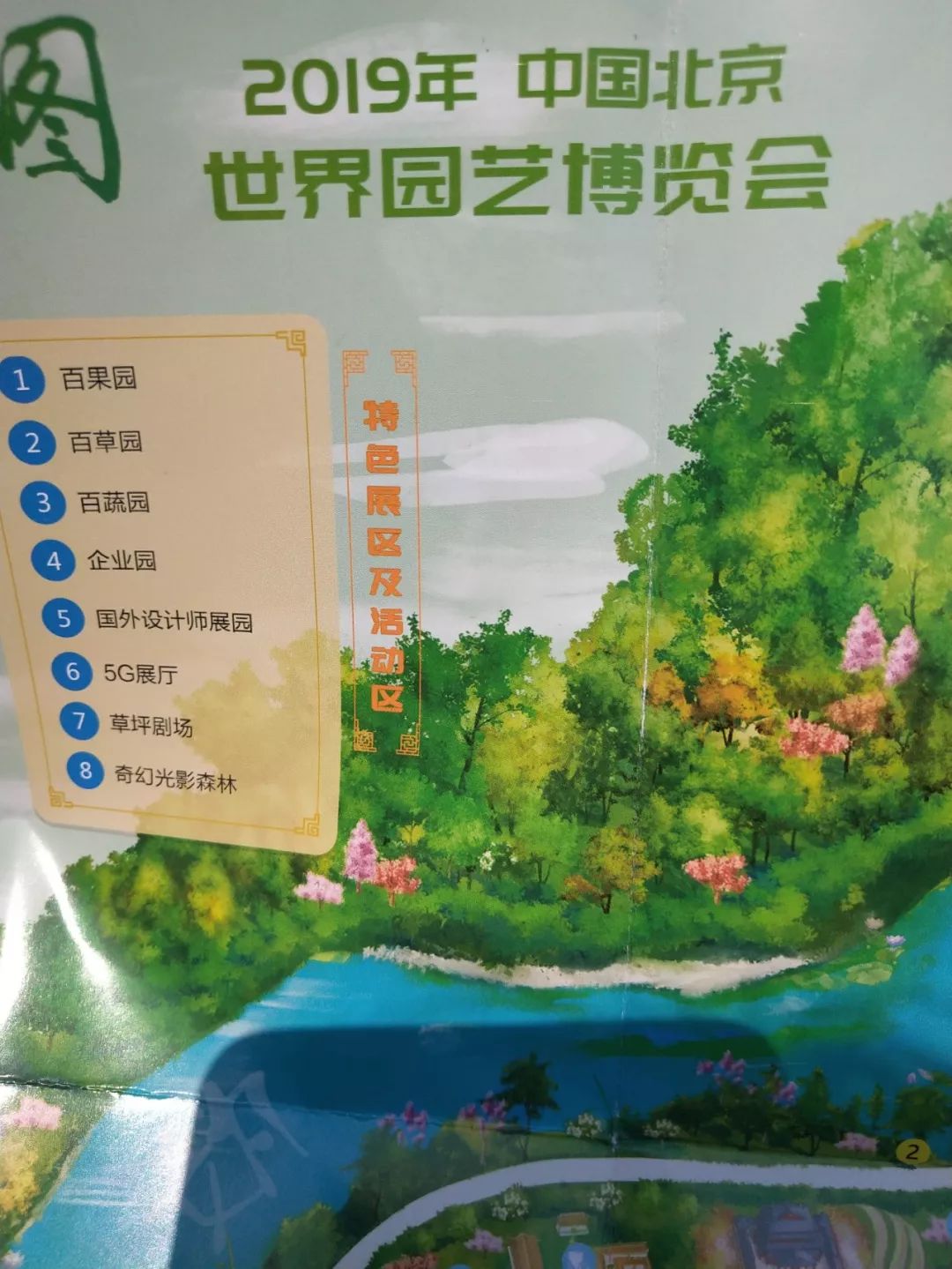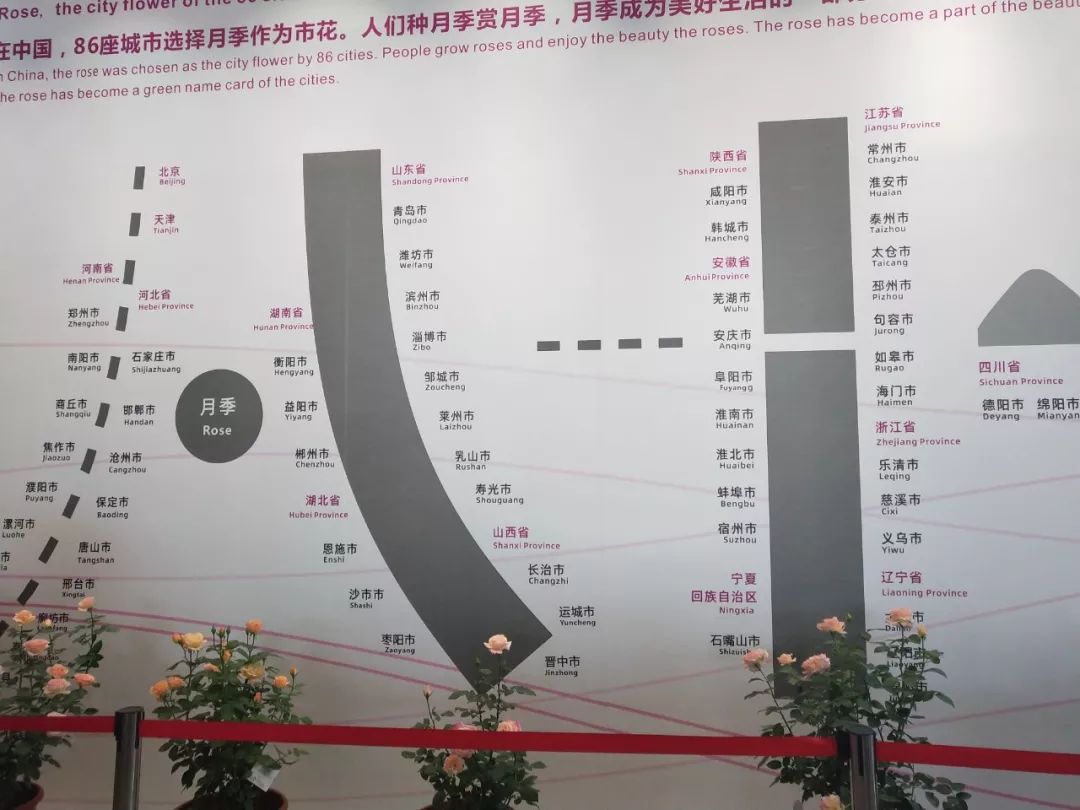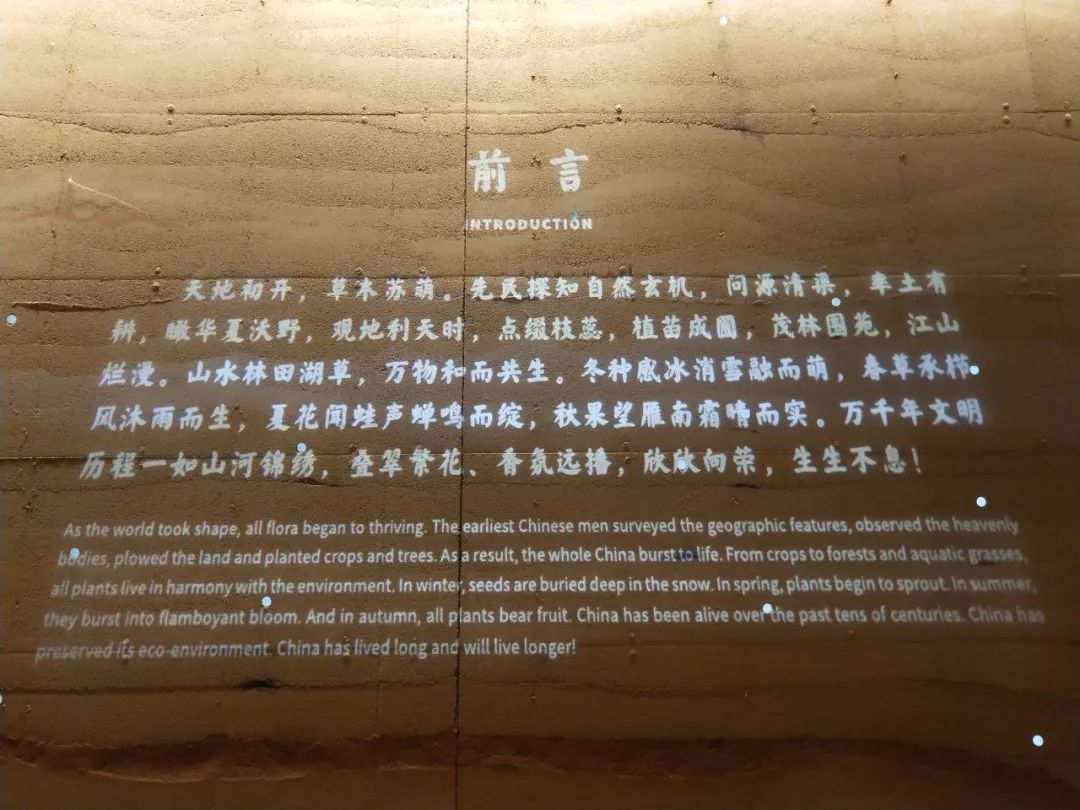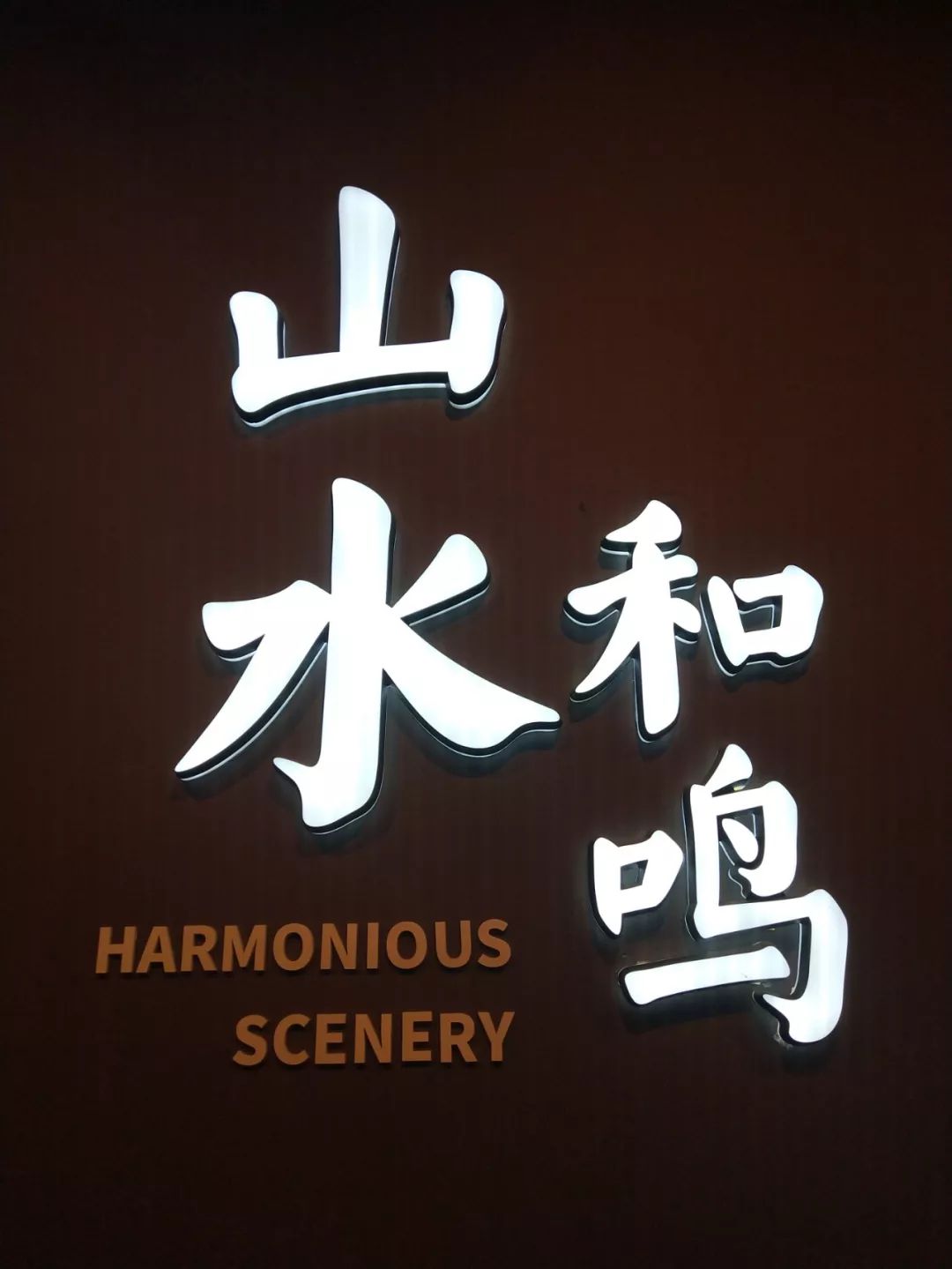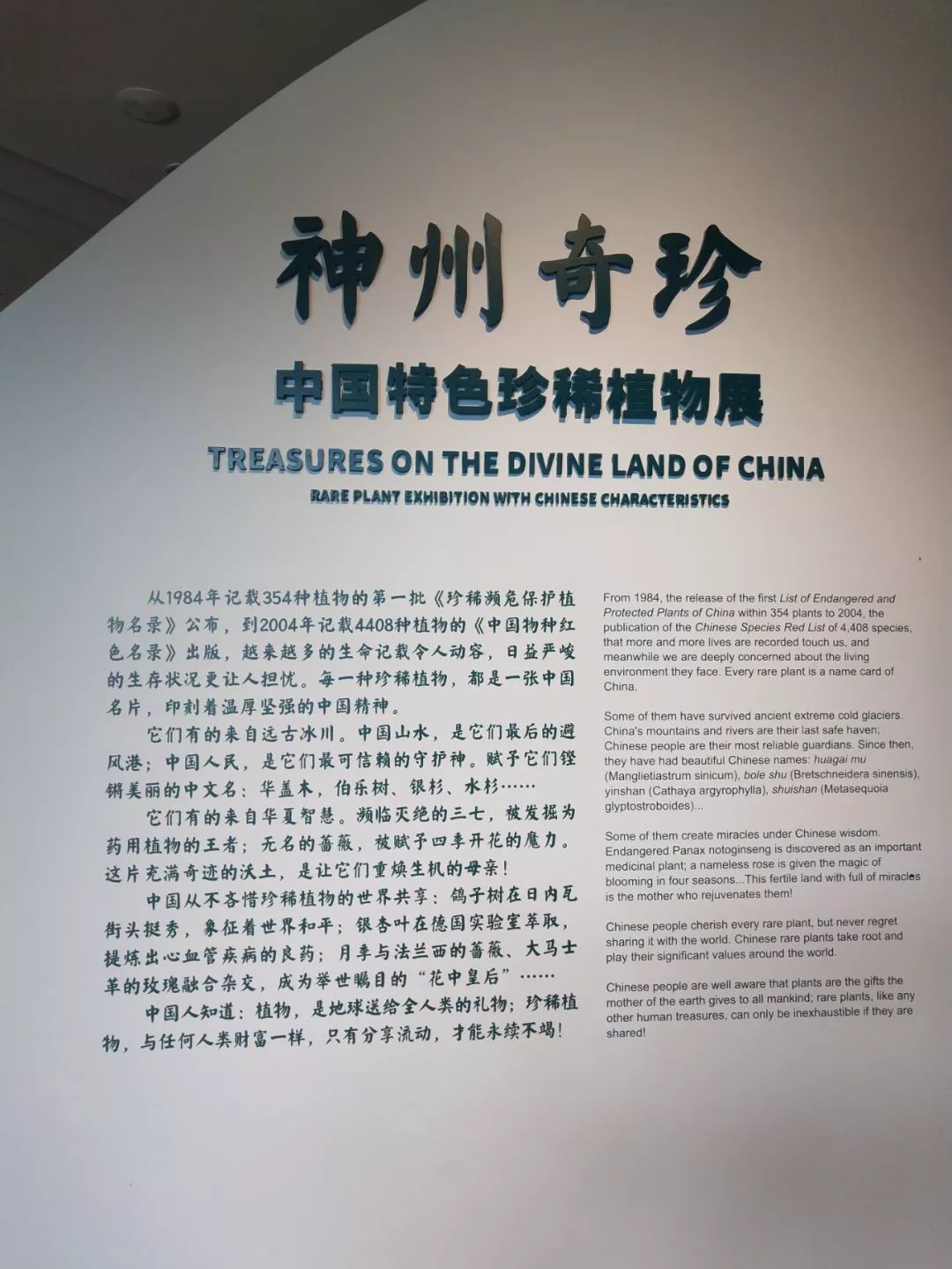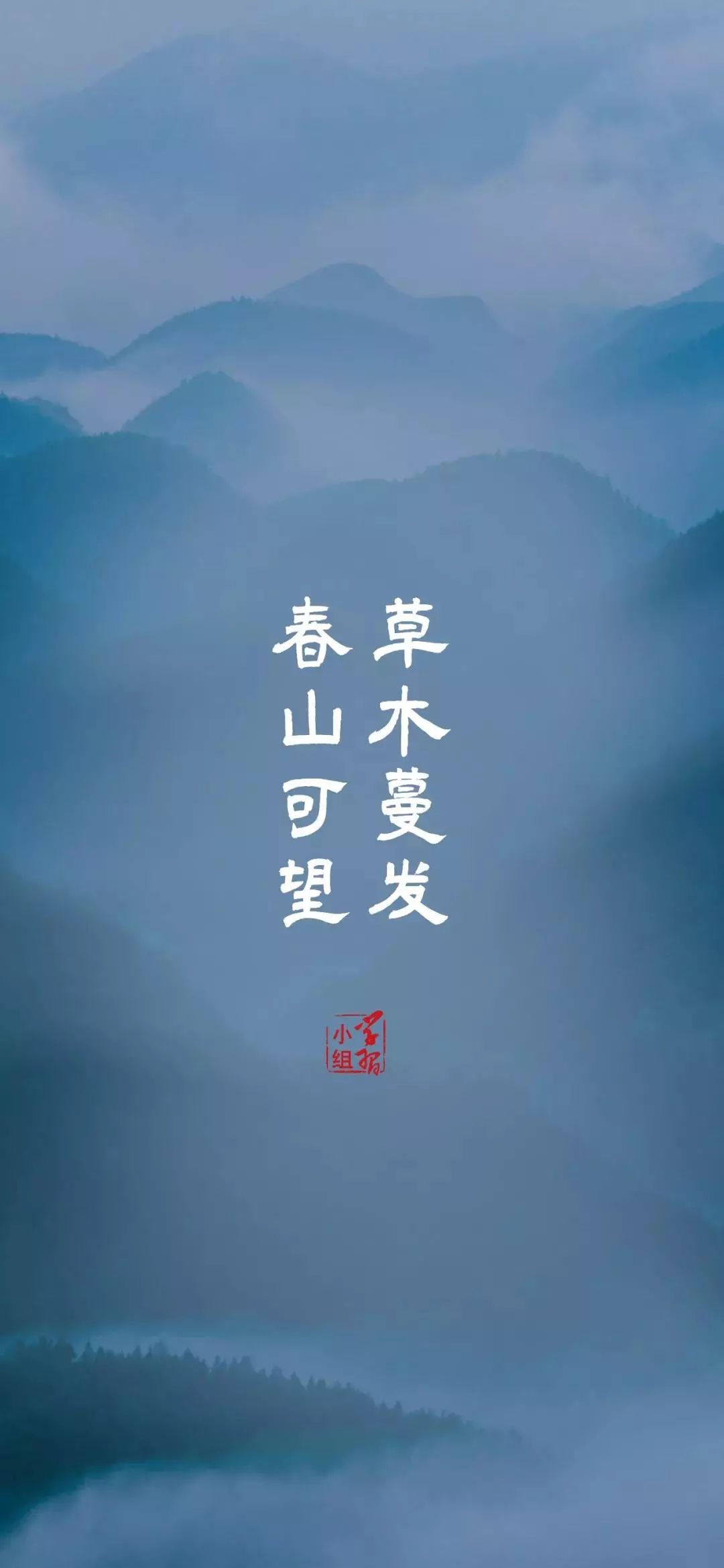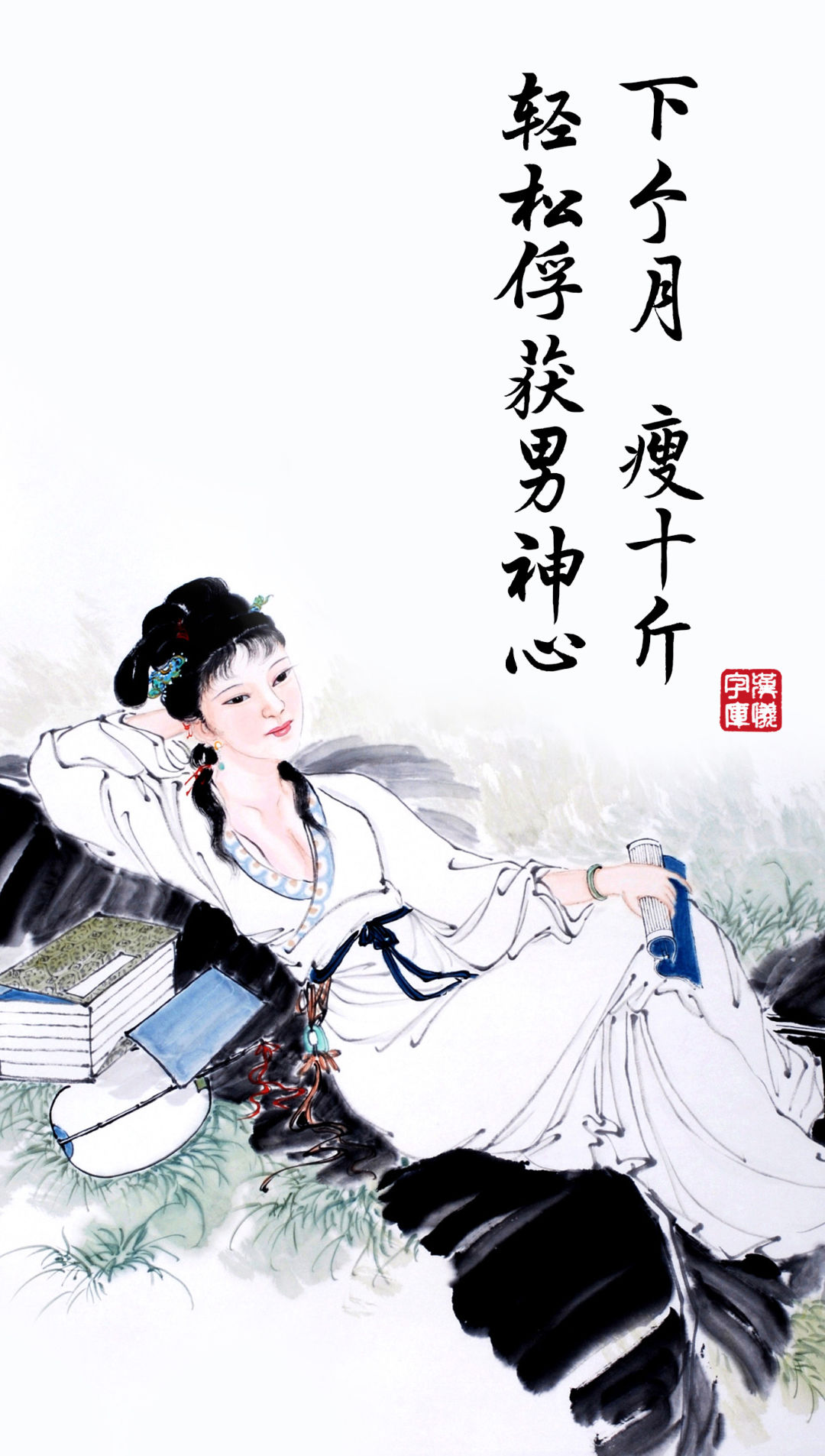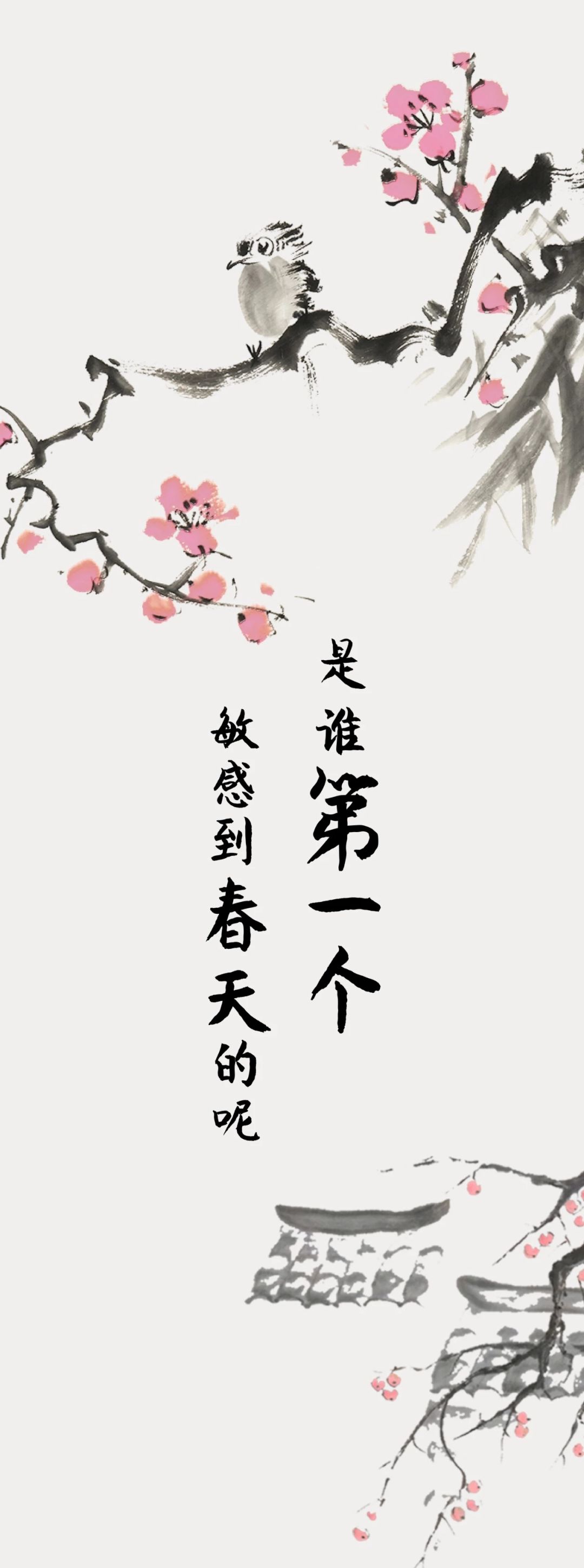
有了这些字体,你的设计自带100年气场~
周末柚子冒着生命危险去了一趟世园会,又挤又累又晒,感觉身体被掏空~
不过还是有收获的,发现了很多字由的字体,比如一进园的引导图,这不庞门正道标题体?
接着国际馆,我还在月季展区看见了大大的汉仪阿尔茨海默病体~
当然最精华,也是排队最久的中国馆必须是C位,地下一层全被汉仪颜楷承包了~
由此我又想到,要表达这种文化内涵的场景,除了颜楷,还有哪些字体?
▲汉仪古隶
▲汉仪苏泽立行楷精修版
▲汉仪北魏写经
▲汉仪意宋
▲汉仪李国兴行楷
▲汉仪新蒂维摩诘经
▲汉仪南宫体